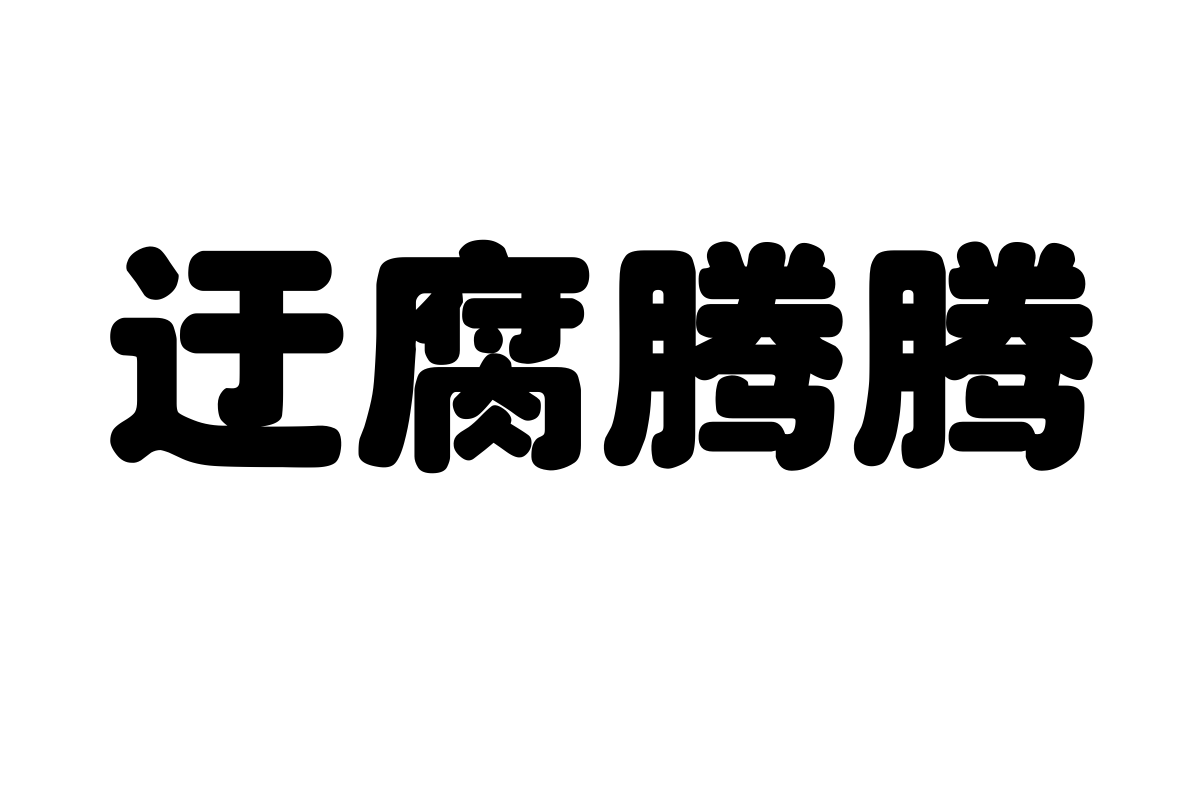
汉仪超粗圆简是一款具有强烈视觉冲击力的中文字体,适用于需要强调文字力量和速度感的设计场景。这款字体以其独特的字形设计和强烈的视觉冲击力而著称,能够有效地吸引观众的注意力并传达出强烈的信息。
汉仪超粗圆简的特点在于其粗壮的笔画和圆润的字形结构,使得整个字体看起来既饱满又有力。这种设计使得该字体在视觉上具有很高的辨识度,能够在众多字体中脱颖而出。同时,由于其笔画粗细不一,因此也具有一定的灵活性,可以根据设计需求进行调整和变化。
除了其独特的字形设计外,汉仪超粗圆简还具有很好的可读性。虽然它的笔画粗壮,但在排版时仍可以保持清晰易读的效果。这使得该字体非常适合用于需要强调文字力量和速度感的设计场景,如广告、海报、宣传册等。
总的来说,汉仪超粗圆简是一款极具个性和创意的中文字体,适合用于需要强调文字力量和速度感的设计场景。